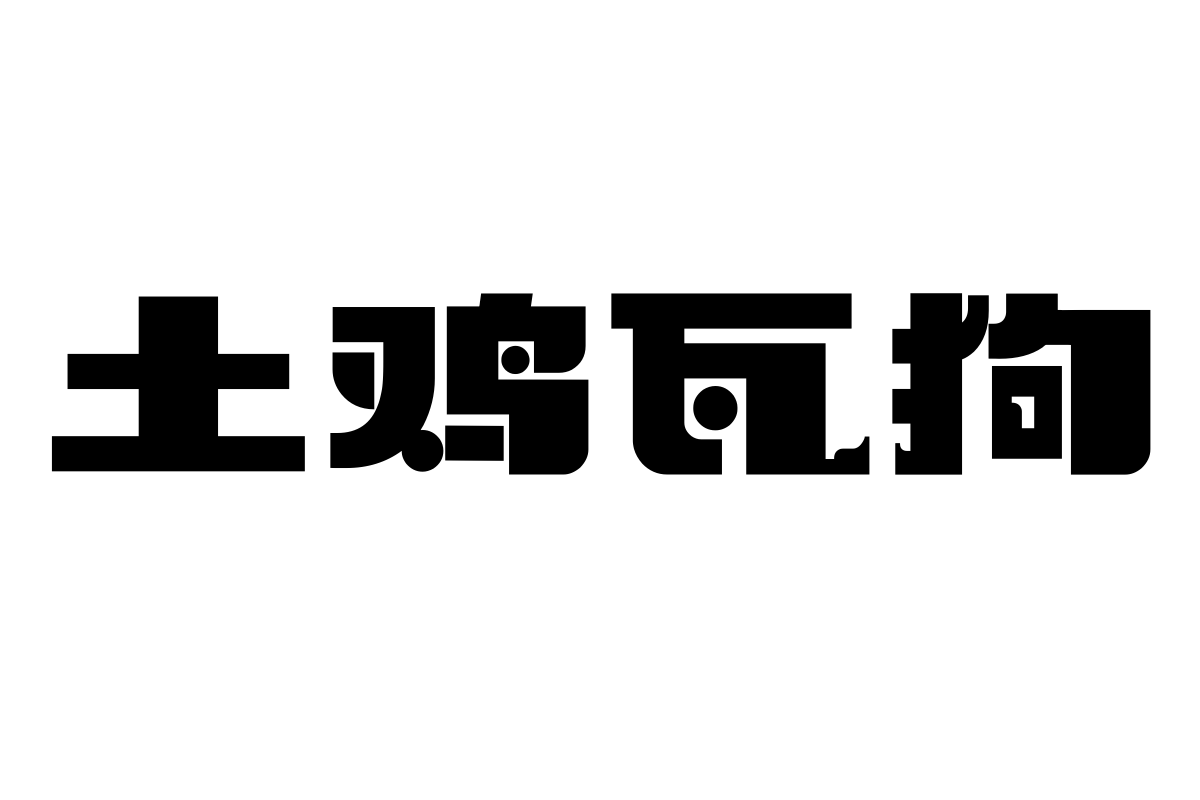
上首非凡体是一种独特的字体,它结合了现代和传统元素,创造出一种既时尚又具有艺术感的字体。这种字体的特点是:
1. 字形独特:上首非凡体采用了独特的字形设计,使得每个字符都呈现出独特的美感。这使得它在阅读时能够吸引人们的眼球,让人印象深刻。
2. 风格多样:上首非凡体可以根据不同的场合和需求进行选择和搭配。无论是正式的文件、广告宣传还是个人博客,都能够轻松驾驭。
3. 易于使用:上首非凡体的设计考虑到了易用性,使得即使是没有专业设计的人也可以轻松使用。这使得它成为了一个非常适合初学者的字体。
4. 可定制性强:上首非凡体不仅提供了多种预设的样式,还允许用户根据自己的喜好进行个性化的调整和修改,使得每个用户都能拥有独一无二的字体。
总之,上首非凡体是一款集美观、实用和个性于一体的字体,无论是在商业还是个人用途中,都能够展现出其独特的魅力。